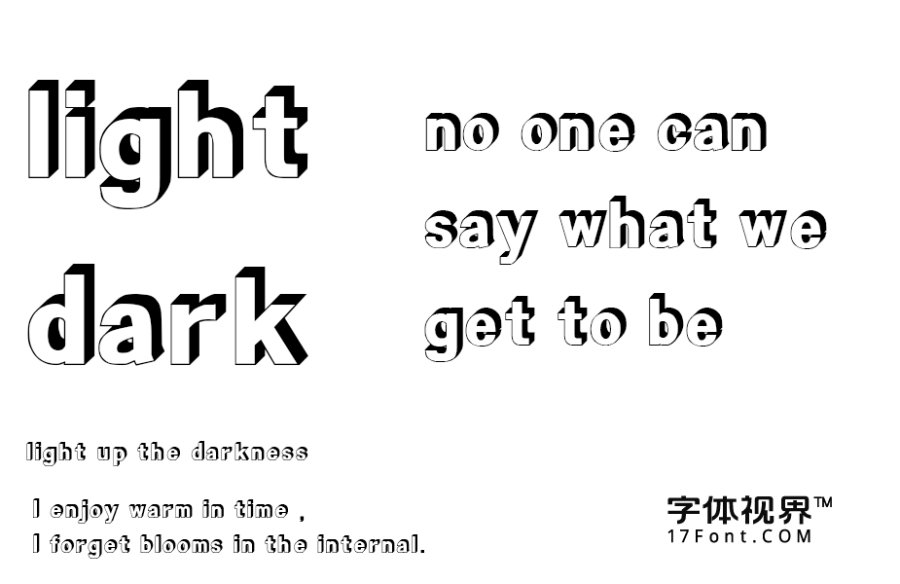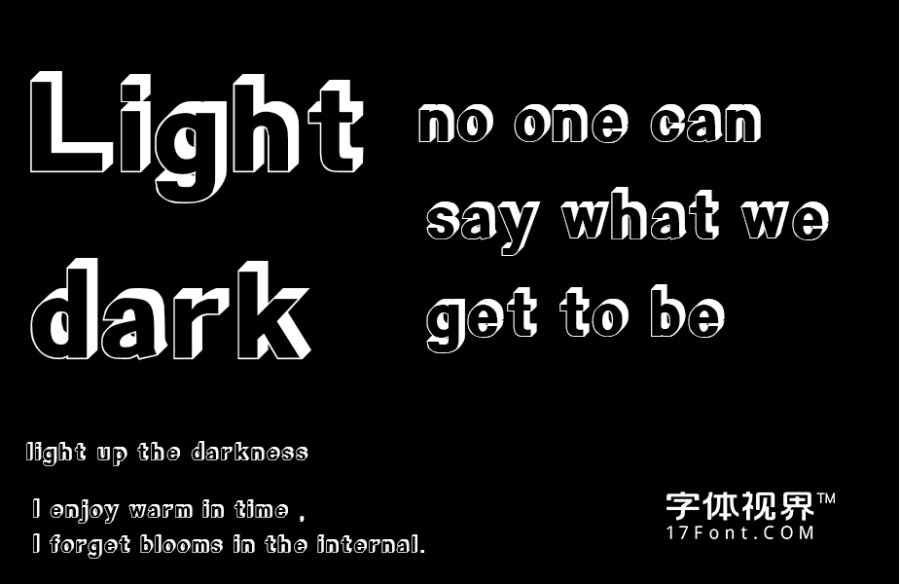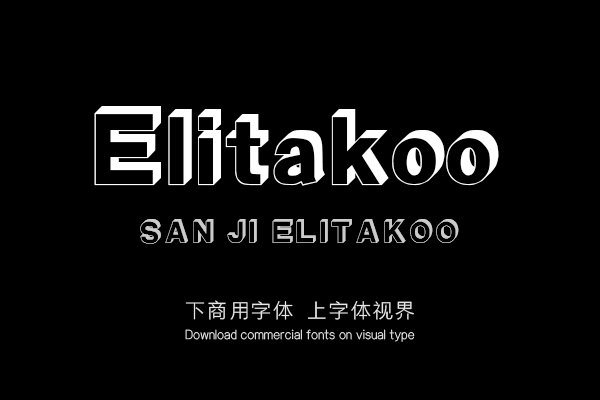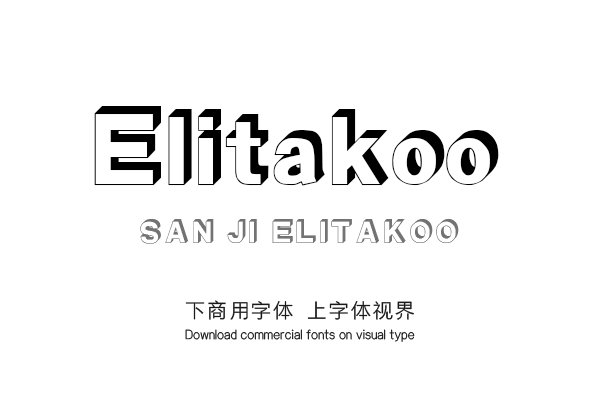
Elitakoo字体为空心立体展示,在直线对角线之间的平衡精心设计,字形厚重清晰。适用于打印和屏幕上,在小标题和标题字中可广泛使用。购买须知:“下载服务费”与“字体VIP”所获得字体 仅用于个人非商用, 商用请联系付费授权。本字体为电脑用字,手机没有root权限不支持直接手机换字(手机如何root,请自行百度搜索教程)。购买前请先 了解清楚后再付款 ,字体为虚拟产品无法回收 一旦购买不支持退款。